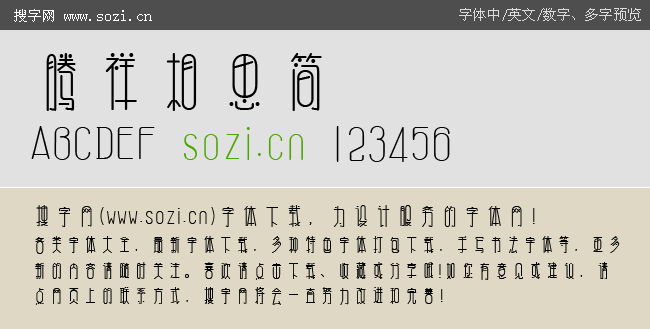
騰祥相思簡
搜字網(wǎng)給大家提供一款騰祥相思簡體卡通中文字體下載。騰祥相思簡是一款應(yīng)用于藝術(shù)設(shè)計方面的中文簡體漢字,該字體筆畫纖細精致、簡潔清晰,每個字風(fēng)格統(tǒng)一,可應(yīng)用于平面設(shè)計、出版印刷、廣告設(shè)計、包裝設(shè)計等領(lǐng)域。